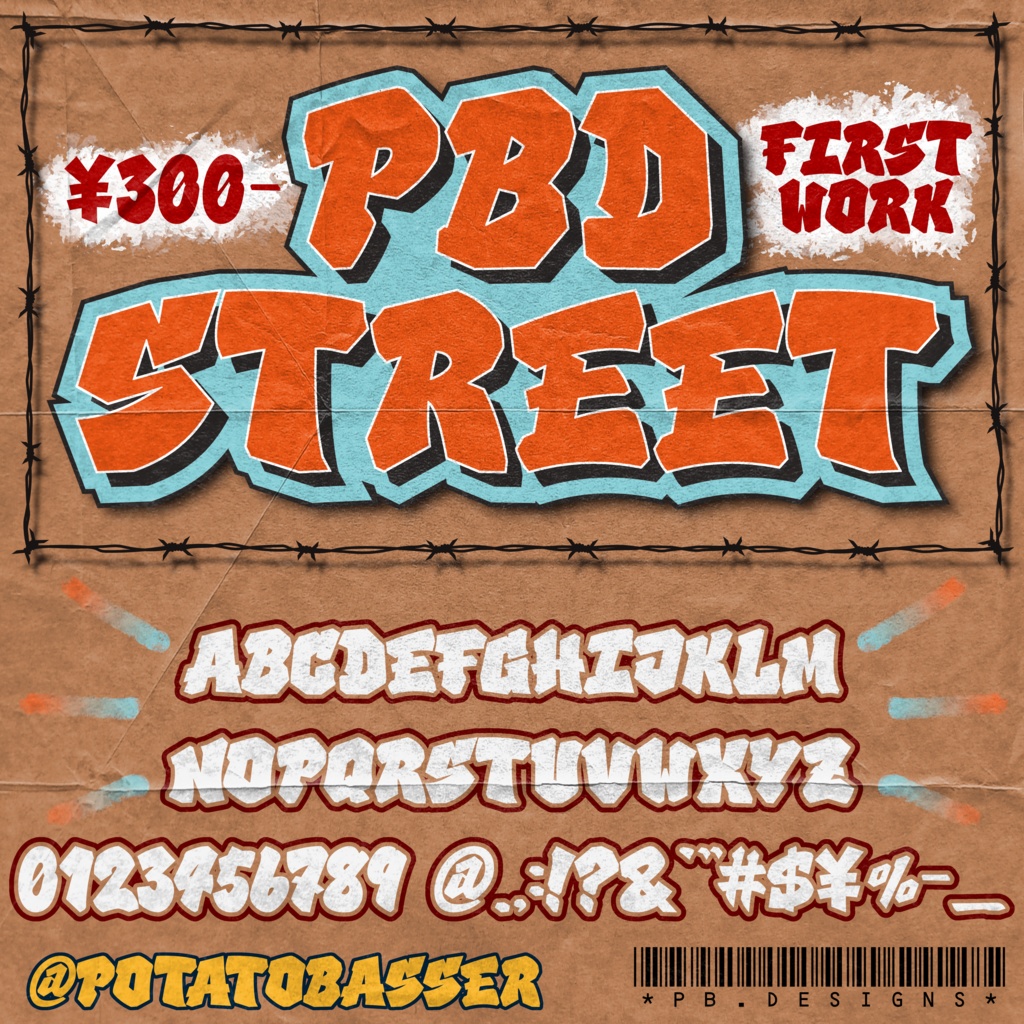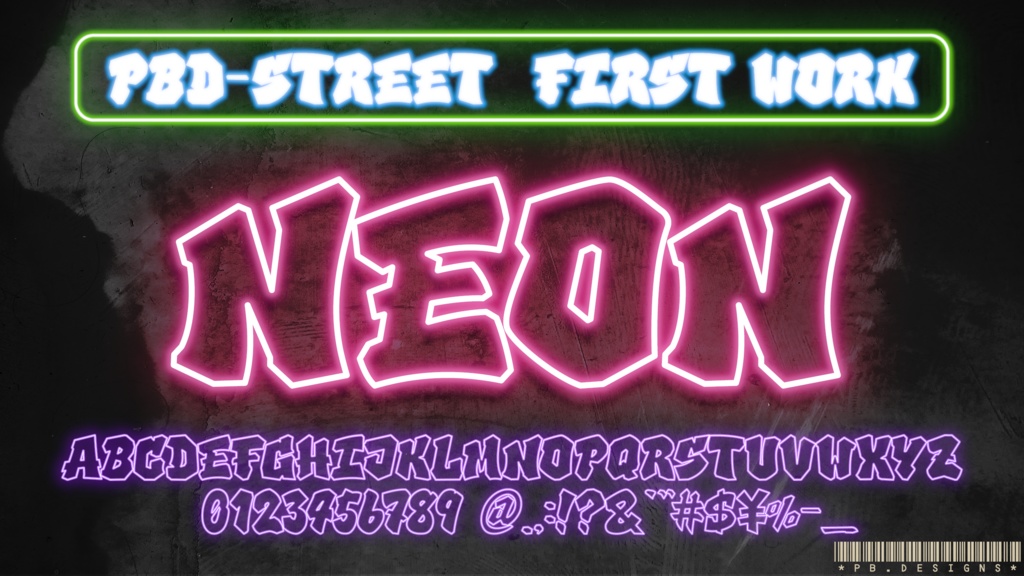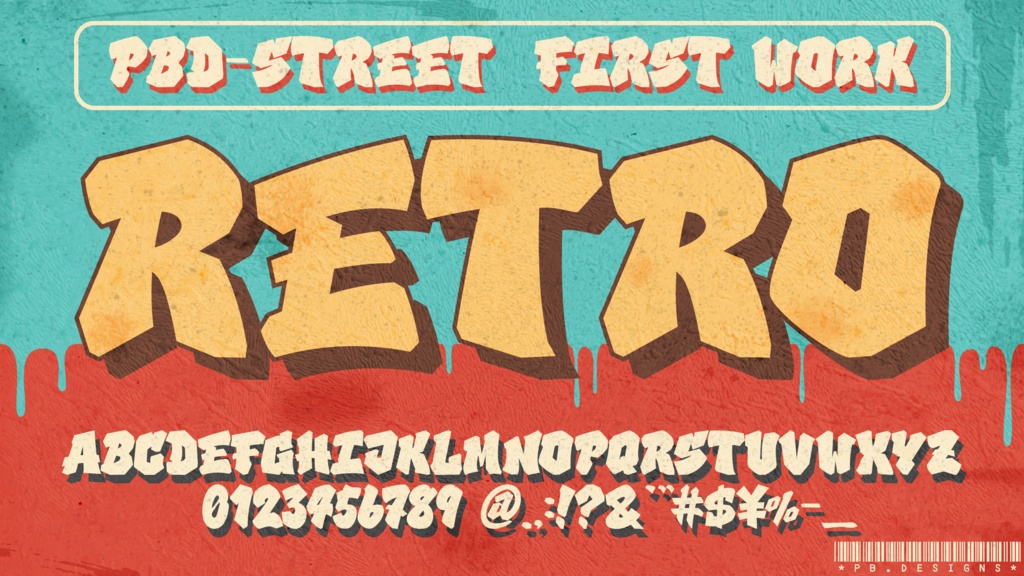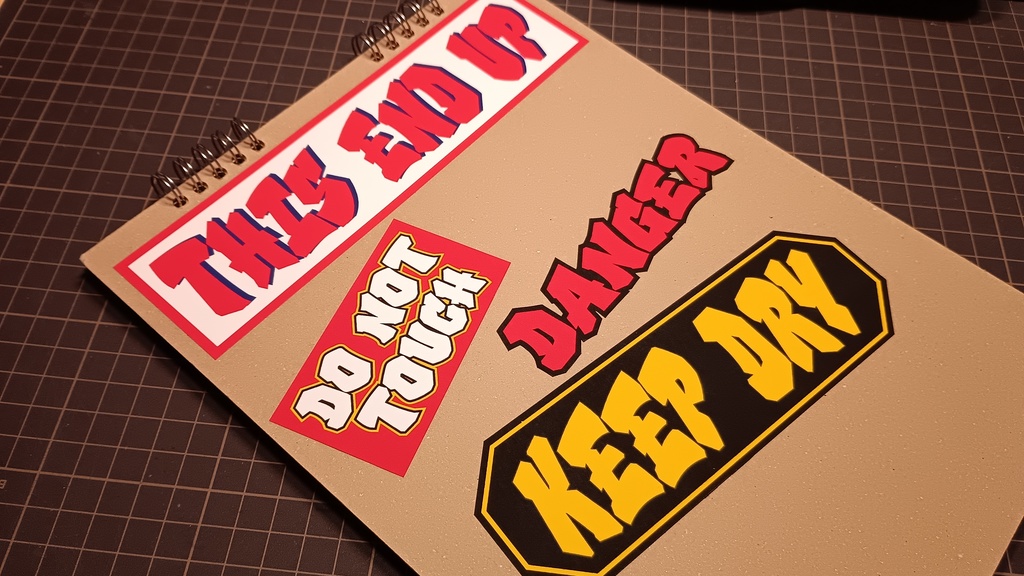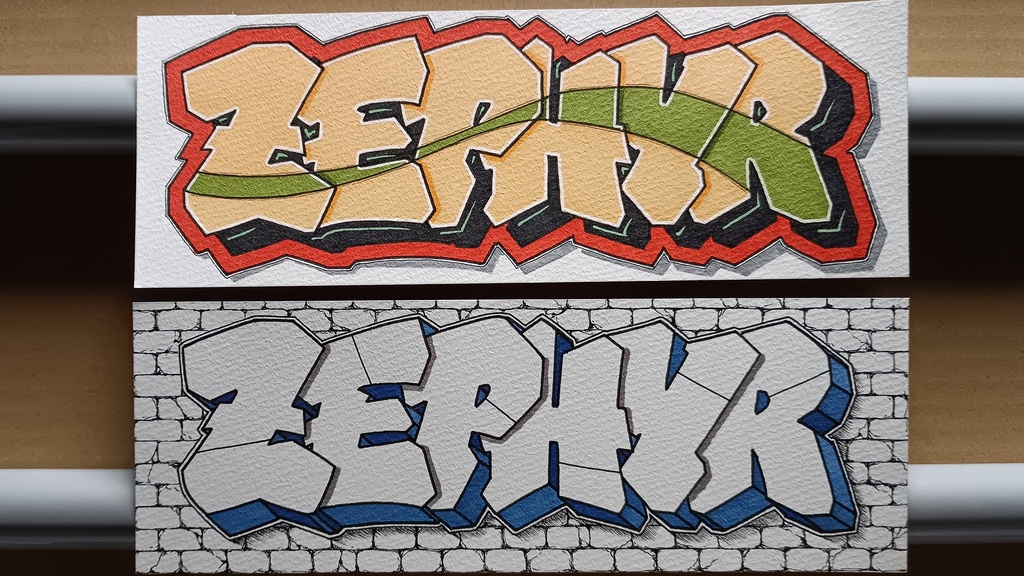
PBD-STREET Font
PB-STREET Font PB-STREET Font(以下PBSF)は、ストリート文化を意識した商用利用可能なフォントになります。 手描きから起こしたPBSFは、さまざまな雰囲気に対応することが出来ます。見本画像にあるような派手なネオンサイン、レトロ調の色合いなど、装飾や色調の変更に対しても馴染みます。 また、太めのしっかりしたボディですので、存在感を活かしたステッカーなどにも出来ます。その存在感は、Tシャツやトートバッグなど、オリジナルグッズの作成にもうってつけです。 収録文字はA~Zの大文字・0~9の数字・数種の記号です。記号には$¥%も収録していますので、値札やセール時のステッカー作成も可能です。 さらに、ストリートの雰囲気を活かし、グラフィティ風のアートを作成する際にも役立ちます。キャラクター画のストリート風の背景を描く時にトレースをして描けば、比較的短時間で雰囲気のあるグラフィティを作成できます。もちろん、見本画像にあるような手描きで描く際にも役立ちます。 PBSFを使用してデザインをする際の注意点としましては、通常のフォントのように使用すると、文字同士の組み合わせによっては、文字と文字の間が狭く(または広く)感じてしまうことがあることです。 本来、グラフィティなどのデザインをする際、次の文字や全体のシルエットに合わせ、その都度に一からデザインをして合わせていきます。ですので、フォントの用に全てが既に決まった形の場合、どうしても組み合わせが難しい場合があります。 なのでPBSFでは、その組み合わせが上手くいくよう、出来折る限りの調整を行っています。 PBSFを最大限に使用するには、文章作成ソフトではなく、ペイントソフトやデザインソフトで変形・装飾などを施すことをオススメします。その為、PBSFは利用規約を通常より緩和しています。 PBSFを使用したイラストやデザインは、私ポテトバサーの各種SNSでも投稿していますので、そちらもチェックしていただけたらと思います。 PBSFは商用利用可能なフォントになりますが、法人の場合は別途で商用利用の追加料金を頂く可能性があります。 ですので、法人で使用する場合は、PBDフォントを購入する前に必ずご相談下さい。